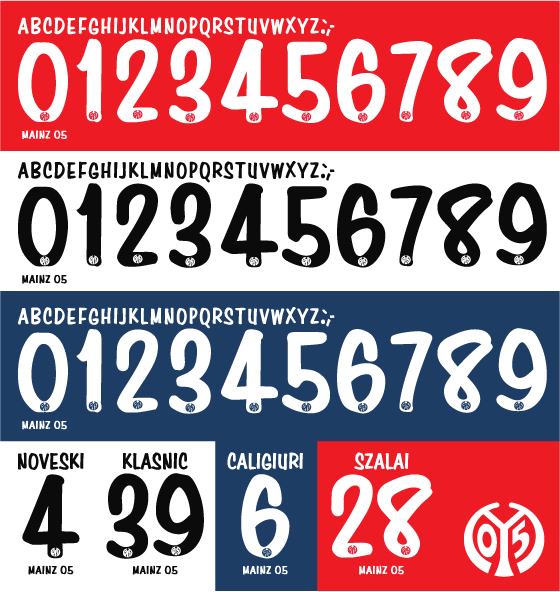
Schrift auf den Mainz 05 Trikots
suche den Namen der Schrift, die für die aktuellen Mainz 05 Trikots verwendet wird. Kann mir hier jemand weiterhelfen? Wäre super :)
Das hatten wir scvhon mehrfach.
Trikot-Schriften werden zumeist für die jeweiligen Sportausstatterm wie Adidas, Puma, Fila, Nike, Kappa und andere speziell für eine Saison entworfen und gleich als Marke registriert, für die richtig großen Vereine wird gelegentlich auch eine eigene Schrift entworfen. Die Schriftarten sind nicht öffentlich verfügbar, und werden höchstens noch an lizensierete Fanartikel-Hersteller vergeben.
Das ist Simpson Condensed Heavy Bold
wohl noch ein wenig aufgefettet.